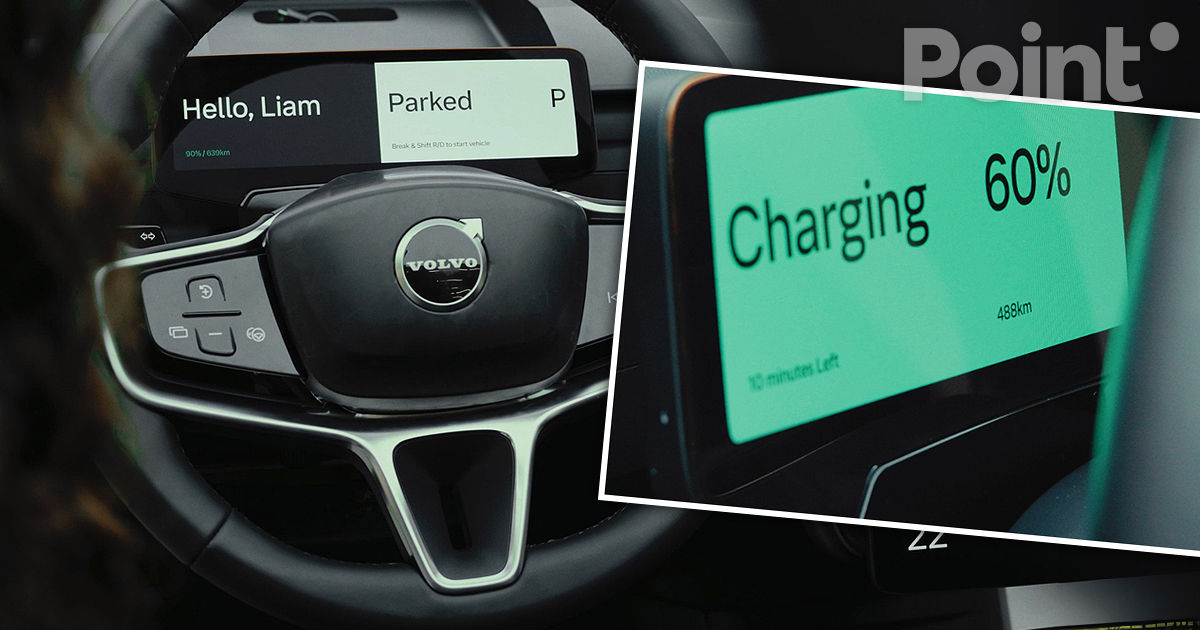
Volvo a creat un font ușor de citit pentru a spori siguranța șoferilor
Volvo a dezvoltat propriul font pentru interfețele auto, orientat către o lizibilitate maximă și reducerea stresului pentru șofer. Noul font a primit numele Volvo Centum.
Fontul a fost creat în colaborare cu studioul de design tipografic Dalton Maag. Scopul său principal este de a transmite informația astfel încât șoferul să poată citi mesajele rapid și fără efort și în condiții dificile de iluminare. Volvo subliniază că proiectul este direct legat de filosofia siguranței, care rămâne un principiu esențial al companiei de aproape un secol.
Potrivit directorului creativ de UX al Volvo Cars, Matthew Hall, Volvo Centum a fost dezvoltat cu accent pe claritate și intuitivitate. Fontul simplifică percepția informației, reduce zgomotul vizual și ajută șoferul să se concentreze pe drum, nu pe ecran.
În procesul de creare a fontului, echipa a ținut cont de particularitățile percepției vizuale și ale psihologiei cognitive. Atenția a fost acordată diferențierii simbolurilor, spațiilor deschise între litere și altor detalii tipografice care facilitează scanarea rapidă a textului. A fost abordată separat și reducerea încărcăturii cognitive – modul în care creierul procesează informația în timpul conducerii.
De asemenea, s-a ținut cont de impactul fontului asupra mișcărilor ochilor, așa-numitele saccade. Forma literelor, combinațiile lor, dimensiunea și dispunerea pe interfață au fost alese astfel încât privirea să se deplaseze fluid pe ecran și să recunoască mai multe cuvinte dintr-o singură privire. Aceasta influențează direct viteza de citire și înțelegere a informației.
Numele Volvo Centum face referire la centenarul brandului, pe care Volvo îl va sărbători în 2027. Debutul fontului este programat pentru începutul anului 2026 – acesta va apărea pentru prima dată pe noul crossover Volvo EX60.
Pe lângă funcționalitate, fontul transmite și o legătură vizuală cu istoria brandului. Volvo precizează că, în crearea formelor literelor, designerii s-au inspirat din modelele clasice, inclusiv Volvo 850 din anii 1990. În contururile fontului pot fi recunoscute aluzii la stopurile verticale, diagonala centurii de siguranță cu trei puncte și simțul proporțiilor caracteristic automobilelor mărcii.